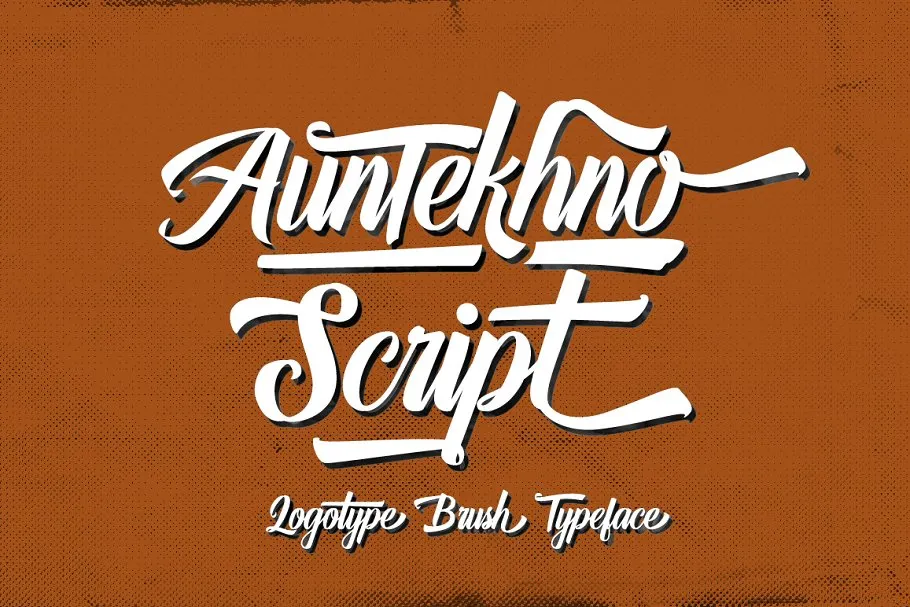
A Auntekhno Font é uma nova tipografia de tração de esfera lançada pelo designer 0001themes, que traz uma nova perspectiva para a criação de logotipos e design gráfico moderno e fresco. Este script font é baseado em calligrafia moderna, adicionando alternativas de traço e traços finais e principais, tornando-o ideal para qualquer projeto de excelente qualidade. Auntekhno destaca-se pela sua característica versátil de tipografia aberta que inclui traçados à mão e estilos de tração de esfera. Perfeito tanto para design gráfico como elementos do design, festas e eventos, camisetas, logotipos, selinhos, adesivos e qualquer projeto ambicioso. Auntekhno Script é a escolha perfeita quando você procura uma fonte de script que oferece não só estilo vintage, mas também elegância natural.